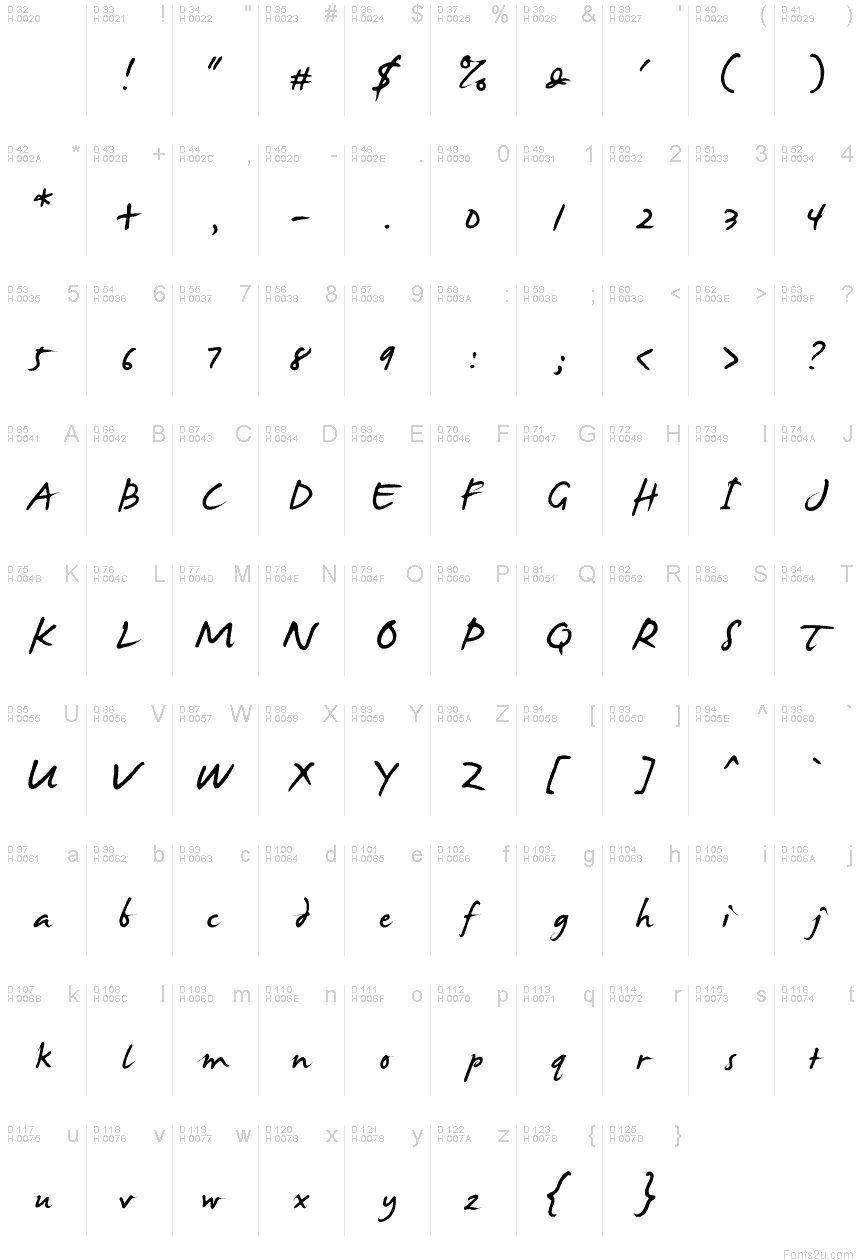
James Fajardo è un font calligrafico gratuito che trasmette l’energia di una firma rapida e sicura. Tratti spessi e inchiostrati sfumano in curve fluide e affilate, infondendo in ogni parola un senso di movimento e carattere. Le lettere si collegano in modo naturale, con quel pizzico di irregolarità che le rende autenticamente umane, evitando un aspetto troppo perfetto o meccanico.
Utilizzare James Fajardo dona un tocco audace e personale a loghi, confezioni di prodotti, poster, copertine di libri, grafiche per social media e inviti a eventi. Questo font gratuito dà il meglio di sé se usato in grandi dimensioni, dove la texture dei suoi tratti e le forme sinuose possono esprimersi al meglio. Accostalo a un font sans serif pulito per il testo di supporto e lascia che James Fajardo si occupi dei nomi, dei titoli e delle brevi frasi che necessitano di un tocco autografo.